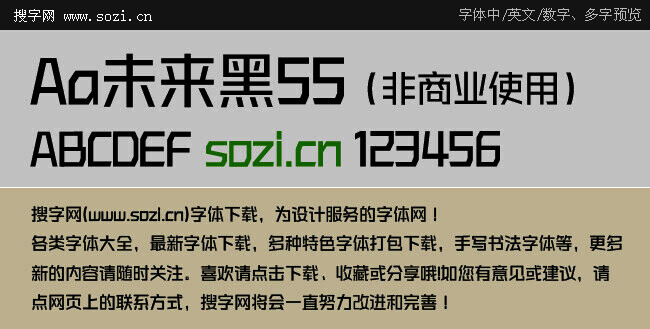
Aa未來黑55
搜字網給大家提供一款Aa未來黑55(非商業(yè)使用)中文字體下載,該字體是一款藝術黑體,字體筆畫粗細一致,運筆自然流暢,結構清晰易識讀,以簡單斜切的筆畫和方正飽滿的結構,來體現機械冷靜卻充滿力量的科技感,適合書裝設計、包裝、海報設計等應用(此字體為個人非商用版,商用可以聯系QQ:1006760504)。